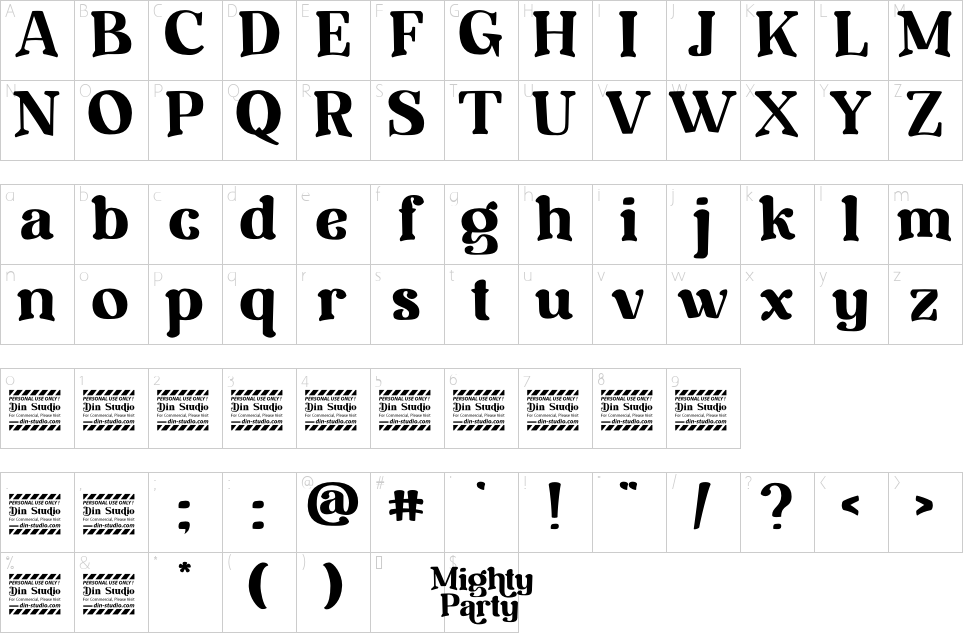
Descubra a deliciosa atmosfera da festa com Mighty Party Font, uma fonte única e divertida disponível aqui para baixar gratuitamente. Desenvolvida pelo designer Natha Type, essa fonte é perfeita para aqueles momentos de descontração e entusiasmo. Não é à toa que a fonte Mighty Party tem sido baixada mais de 1.978 vezes, mostrando sua eficácia em criar ambientes festivos e animados. Se você é fã de fontes divertidas e coloridas, essa fonte é o item perfeito para adicionar um toque especial a seus projetos digitais. Não espere mais, adquira a Mighty Party Font hoje e prepare-se para criar textos festivos que farão seu público rir e dançar.